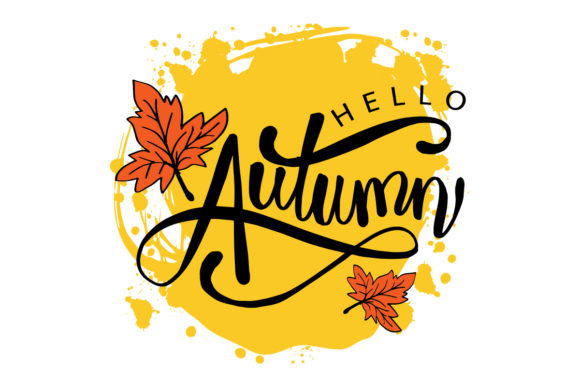
Hello Autumn Hand Drawing Caliigraphy
Jika anda sedang mencari aset berkualiti tinggi seperti Hello Autumn Hand Drawing Caliigraphy, pakej premium ini merupakan pilihan yang hebat untuk projek kreatif anda.